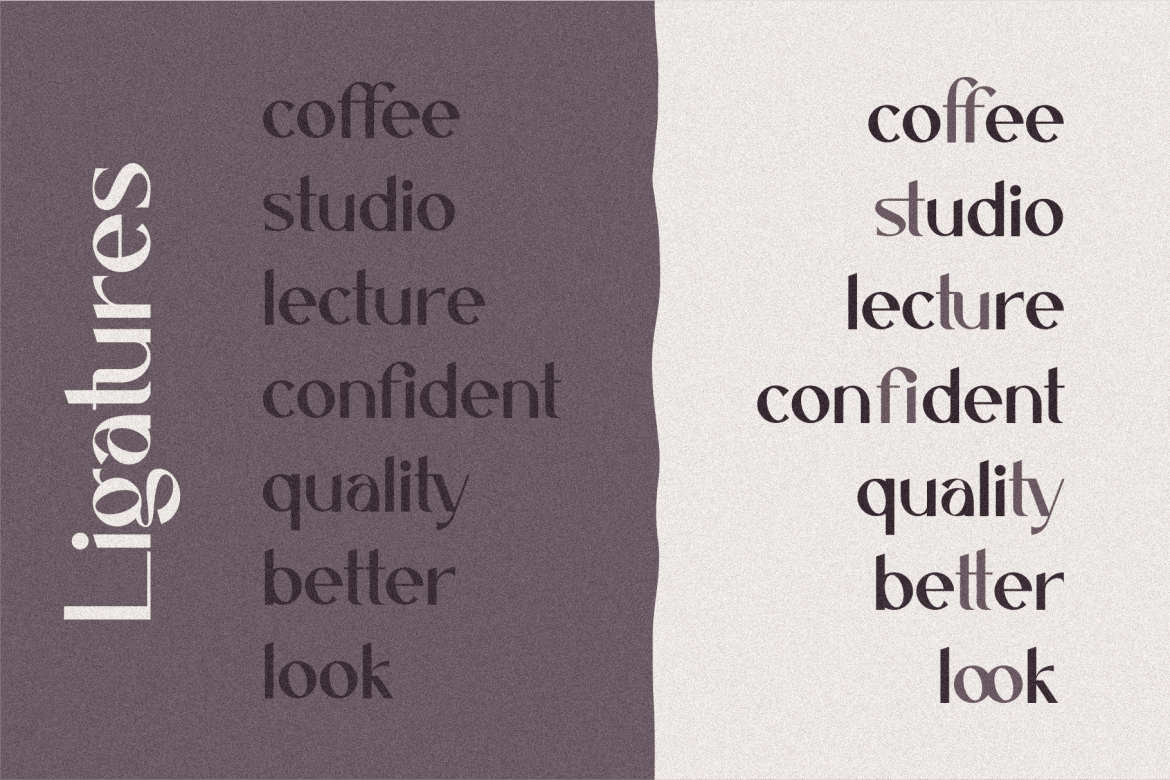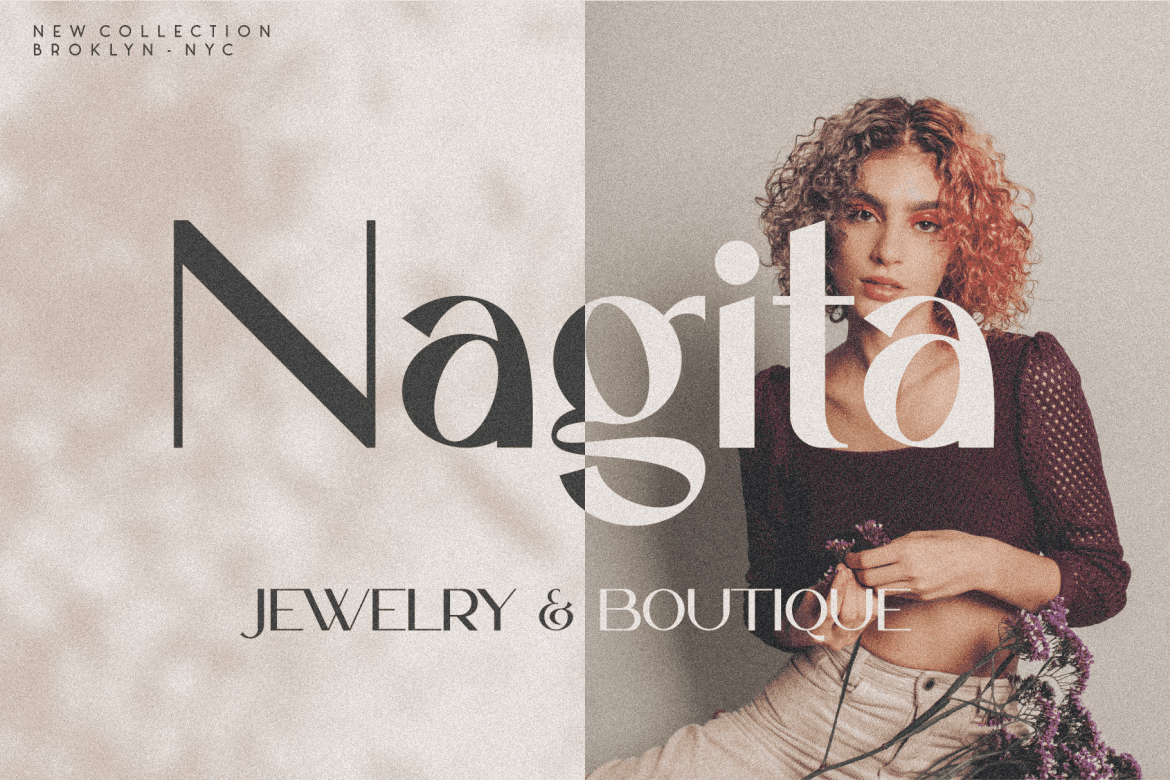
Font Caligna Việt Hóa - Font chữ hiện đại
Font Caligna Việt Hóa - là một font chữ mang phong cách độc đáo, hiện đại và sang trọng phù hợp trong hầu hết các thiết kế như thời trang, ẩm thực, khách sạn, nhà hàng. Phông chữ được áp dụng cho logo, dòng tiêu đề ngắn, thiết kế nhãn...